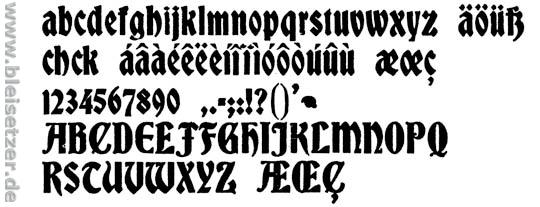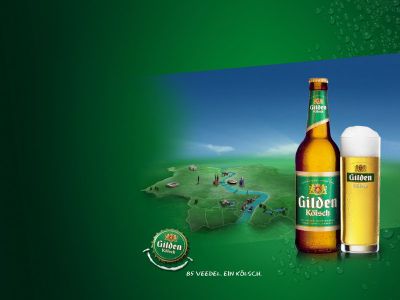
Gebrochene Schriften, noch aktuell?
Befinde mich derzeit bei der Recherche für mein Diplom. Das Hauptthema sind gebrochene Schriften im 21. Jahrhundert.
Aus diesem Grunde suche ich Verlage, bzw. Publikationen die sich dieser gebrochenen Schriften in den letzten Jahren bedient haben. Kann mir irgendwer dazu etwas sagen.
PS.: Die bekannten Bücher sind mir vertraut (u.a. »Fraktur« [Kapr], »Fraktur mon Amour«), ich suche eher die nicht so leicht zugänglichen Publikationen (Sonderausgaben, Jubiläumsausgaben, bibliophiles etc.)
Vielen Dank für die promten Hinweise – Das Buch Hiob, ist soweit ich weiß nur auf dem Titel in gebrochener Schrift gestaltet. Ist also nicht nötig extra auf große Suche zu gehen, vielen Dank nochmals.
Habe gerade mein Diplom mit eben diesem Thema abgeschlossen.
Bei mir hieß es "gebrochene Schriften heute".
Habe so eine Art Aufklärungs und Image-kampagne gestaltet,
herausgekommen sind dann 12 Plakate und ein Magazin.
Erst einmal habe ich die Probleme analysiert und dann Lösungsansätze
angerissen und selbst noch zwei Schriften entworfen.
Einen ähnlichen Einsatz der „Fetten Fraktur“ habe ich auch schon in einer Ausgabe der deutschprachigen Basketballzeitschrift „Five“ gesehen. Wenn's wichtig ist, schaue ich gerne nach, welche das war.
Durch die Recherche und Eure Tipps (zwei p oder nicht, bin noch nicht ganz in der neuen Rechtschreibung) bin ich auf den angelsächsischen Sprachraum gestoßen. Dort gibt es ja auch einiges zum Thema. Hat irgendwer schon einmal eine Publikation in den Händen gehalten (aus den letzten Jahren) die sich der gebrochenen Schriftform bedient? Ein paar Titelgestaltungen habe ich schon gefunden, doch vielleicht habt ihr ja noch mehr.
Danke für den Hinweis auf »Das Buch Hiob«, war ein Denkfehler von mir, hab nochmal reingeschaut, das ist wirklich komplett in gebrochener Schrift gesetzt.
Mein Kollege Bernhard Schnelle aus Braunschweig hat mir dieses Muster geschickt:
Es zeigt die "Amerikanische Altgotisch / Bradley":
Bauersche Gießerei, Frankfurt am Main
Erstguß ca. 1908
Basis dieser Schrift war offensichtlich die amerikanische Bleisatz-Schrift "Bradley" von Henry William Bradley (1869-1962) und Joseph Warren Phinney (1848-1934) für das Cover einer Weihnachtsausgabe von "Harper's Bazaar".
"In einem Zeitschriften-Inserat für das Videospiel "saints row"
fand ich zu meiner Überraschung folgende Schlagzeile..."
Dann pack doch den original Firestone-Schriftzug noch dazu. Es stammt ebenfalls von der Amerikanischen Alt-Gotisch / Bradley:
Völlig abgedreht, diese Typen.
Jetzt verwenden Sie beim Internet-Radio die Koch-Fraktur :D
Auch in Köln versuchen sie, dem aufkommenden(?) Trend der Gebrochenen Schriften zu folgen. Leider wurde dann nur ein Erbrochenes Kölsch daraus:
Hiermit rufe ich zu einer Spenden-Kampagne auf:
"Wir schenken den Kölnern ein Lang-s"
Auch wenn mich die Freunde der gebrochenen Schrift jetzt prügeln mögen: könnte es nicht aus Marketingsicht sinnvoll sein den Stilbruch zu begehen auf das lange s zu verzichten weil in der Masse der Zielgruppe die Gefahr bestünde es nicht mehr lesen zu können?
Oh ja.
Und dann könnte man auch gleich noch die Groß-/Kleinschreibung abschaffen und das "ß" sowieso. Es ist wahr jetzt und kein Sarkasmus: Der Neffe meiner Frau ist jetzt im 2. Schuljahr. Er soll Worte so schreiben wie er sie hört. Das wird auch nicht korrigiert. Es kann so stehen bleiben, wie es kommt.
Ich finde das in Ordnung. Und nach der sechsten Flasche Kölsch ist das doch sowieso ejal, hicks.. und in Kölle fällt dat eh nich auf, ne. Wir hier rheinabwärts in Düsseldorf merken das immer montags, wenn die Kölsch-Wasserleichen hier vorbeitreiben. Manche stammeln noch "..Esch möht zu Fooss na' Kölle jonn.."
Joh, joh.. die Kölner.
Wir können es doch nicht zur Normalität werden lassen, daß sich immer dann, wenn etwas vielleicht erklärungsbedürftig ist oder einen Hauptschul-Abschluß als Bildungsgrad voraussetzen muß, um verstanden zu werden, Resignation breit macht und wir die Meßlatte noch niedriger hängen. Das geht doch nicht.